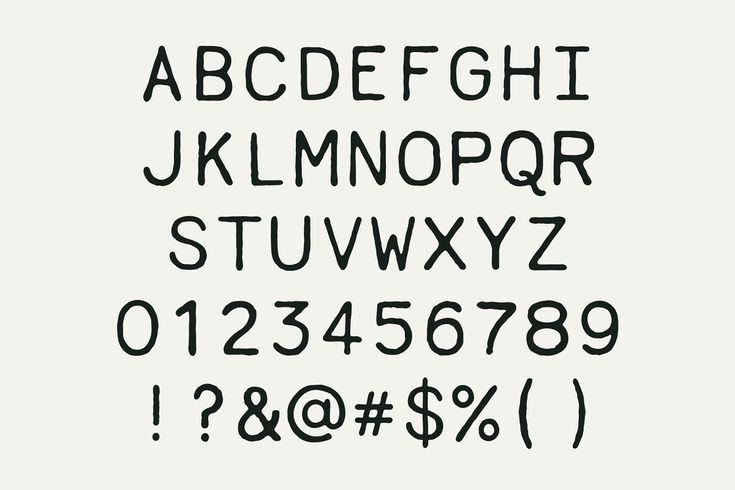
Штамп контактной сети
Штамп контактной сети, представленный CC Marshall, представляет собой приятный причудливый размытый шрифт с полным набором символов, цифр и знаков препинания. Шрифт идеально подходит для заголовков, рекламы, баннеров и многого другого. Catenary Stamp — один из полезных шрифтов для штампов. Попробуйте!